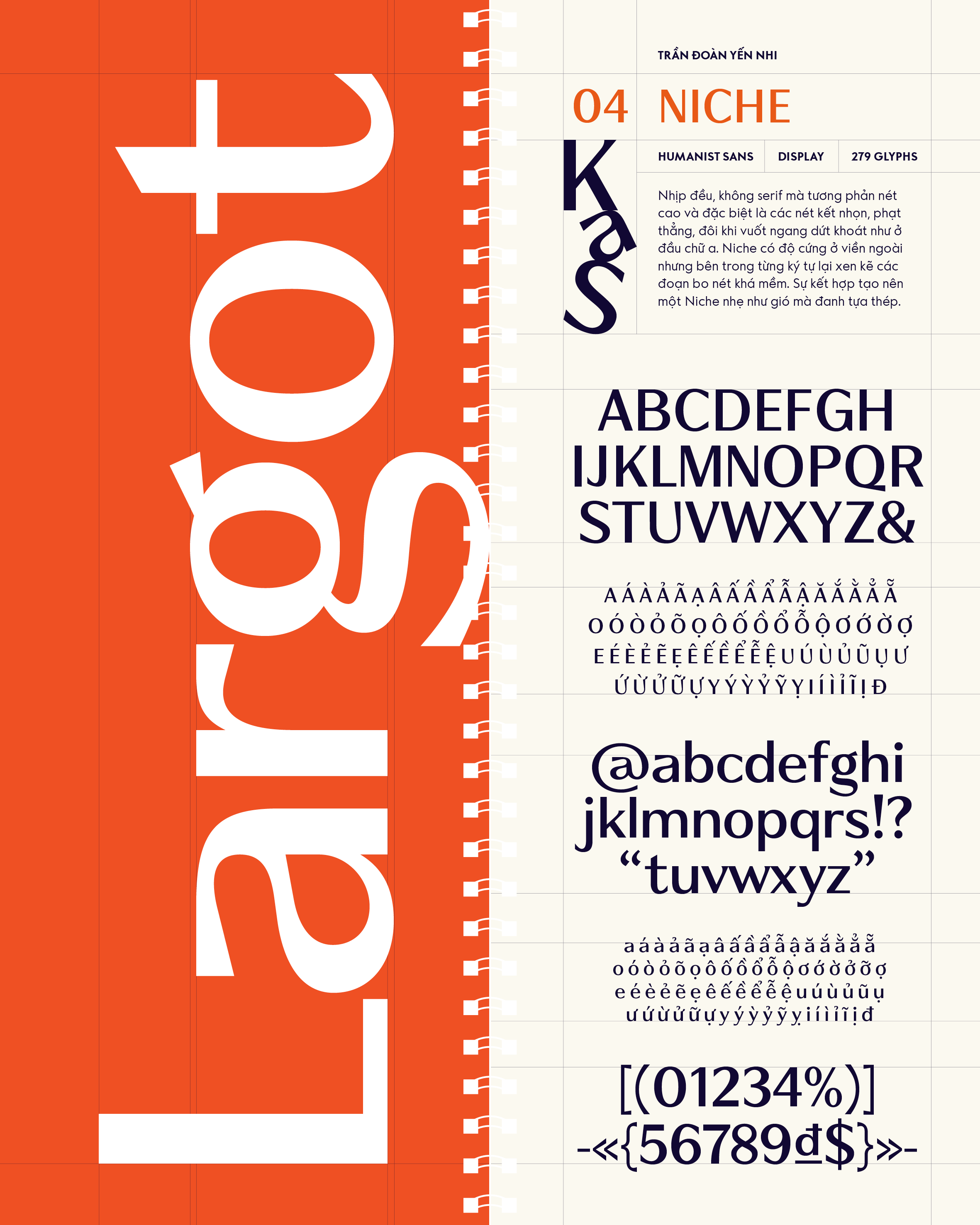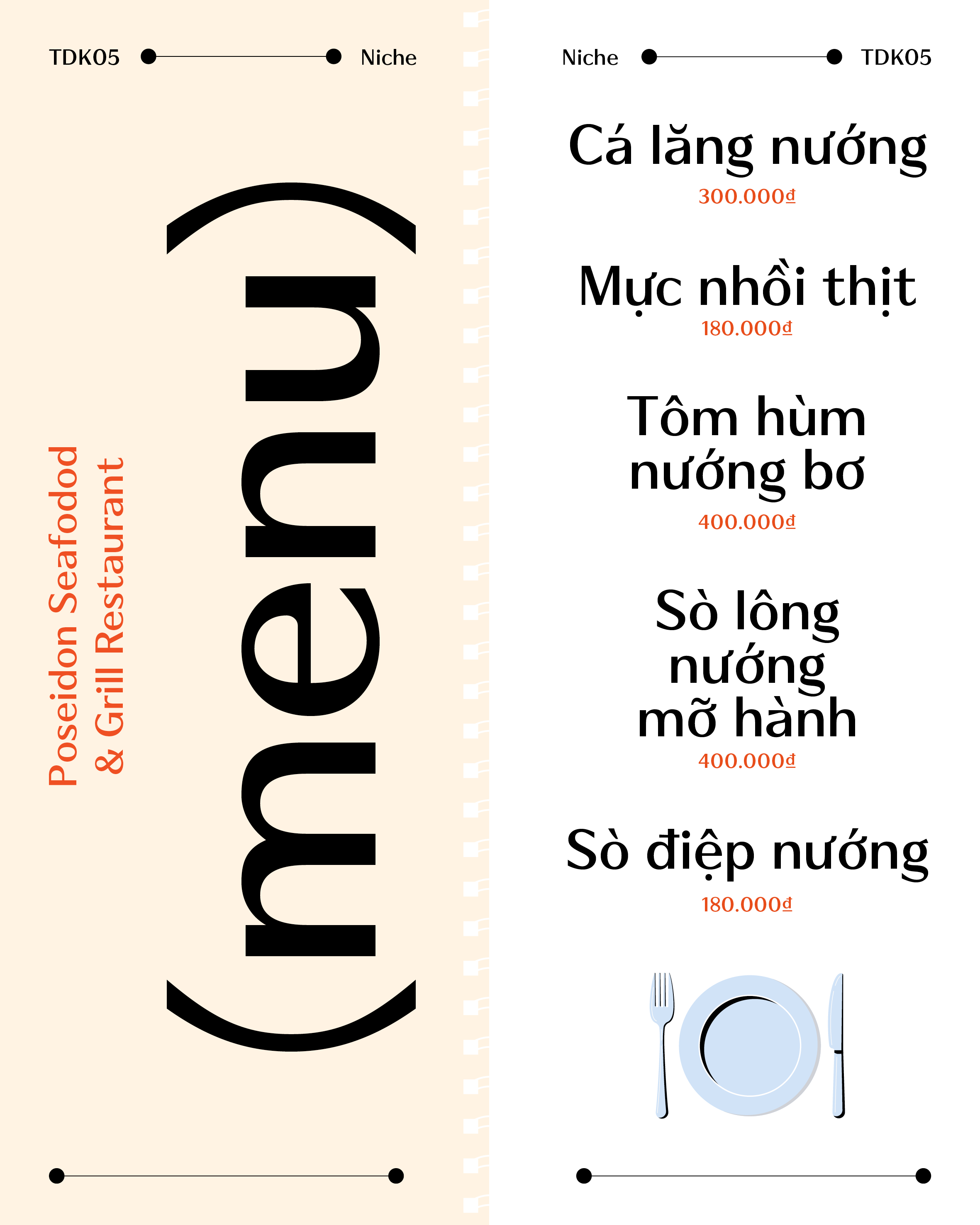
Niche
Về Niche: Nhịp đều, không serif mà tương phản nét cao và đặc biệt là các nét kết nhọn, phạt thẳng, đôi khi vuốt ngang dứt khoát như ở đầu chữ a. Niche có độ cứng ở viền ngoài nhưng bên trong từng ký tự lại xen kẽ các đoạn bo nét khá mềm. Sự kết hợp tạo nên một Niche nhẹ như gió mà đanh tựa thép.
Humanist Sans-serif
Display
Trần Đoàn Yến Nhi